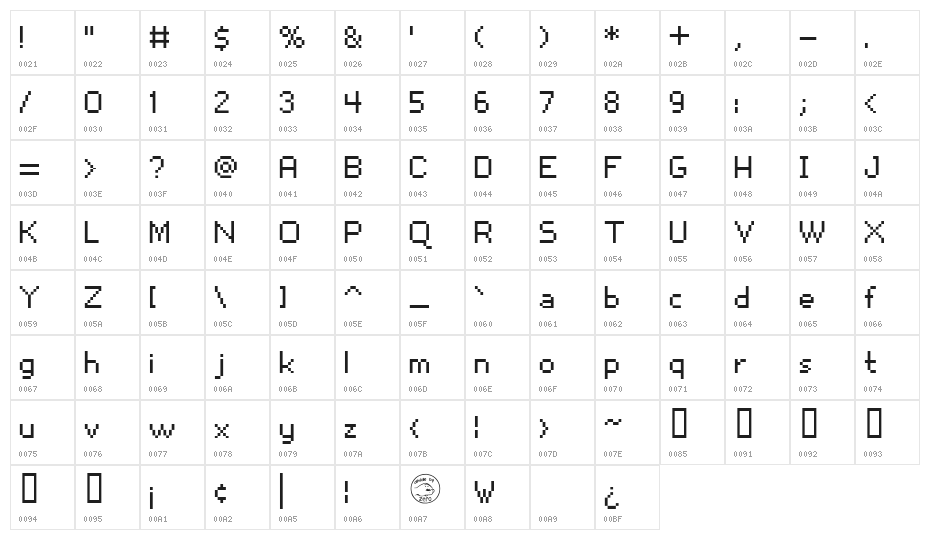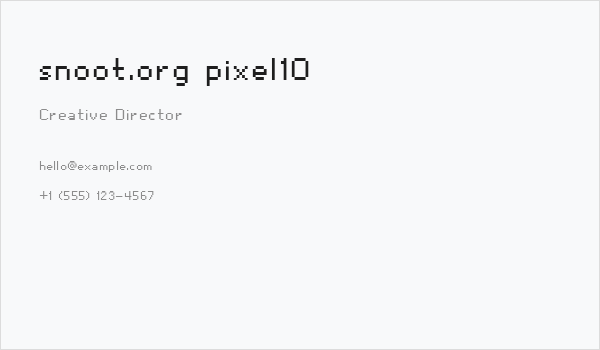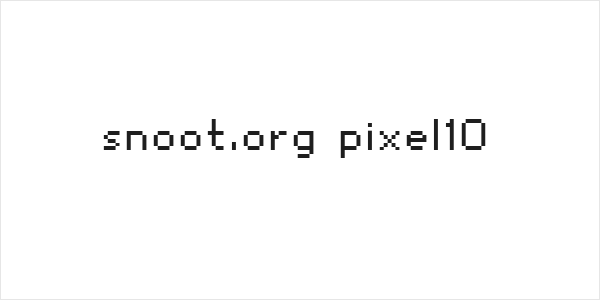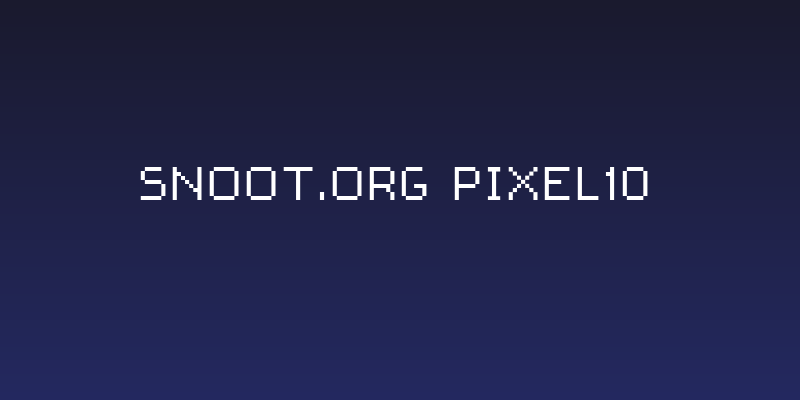
snoot.org pixel10 Font
| Estilo geral | Retro, Digital |
| Caso de uso | Headlines, Logos, Digital displays |
| Projetos propostos | Ideal for video game design, digital art projects, retro-themed websites, and tech-oriented branding. |